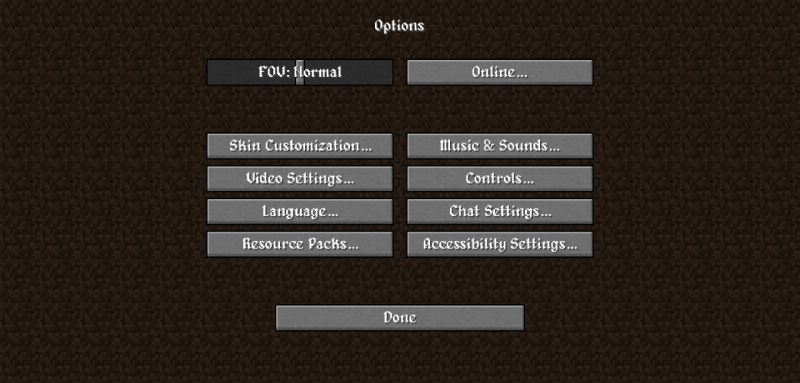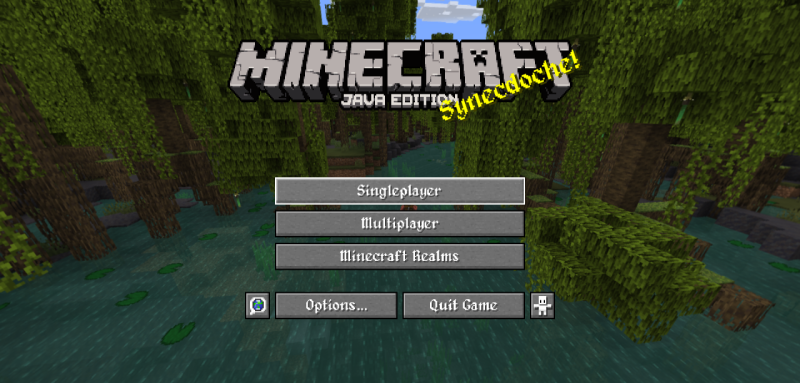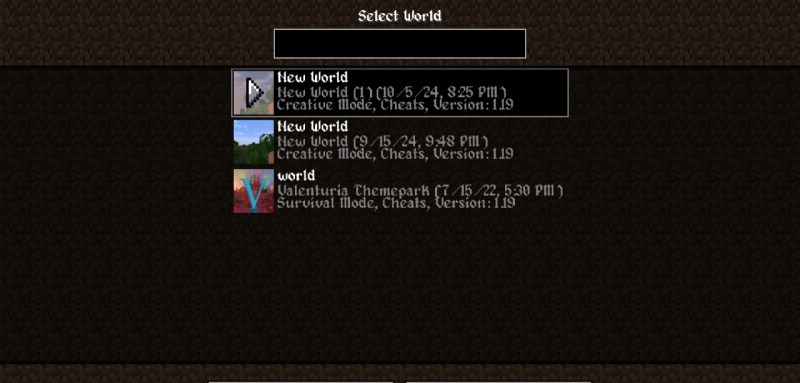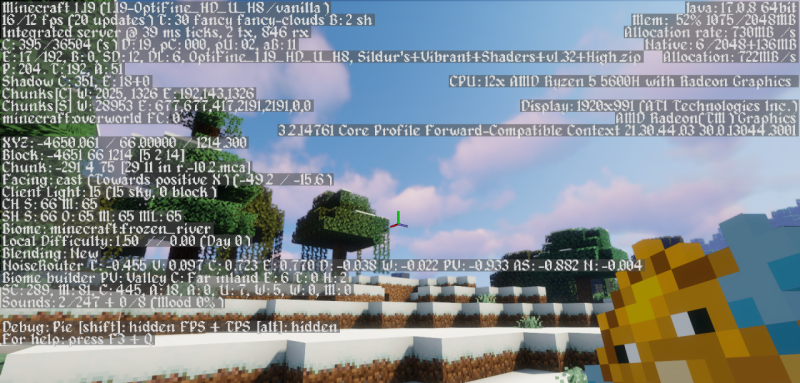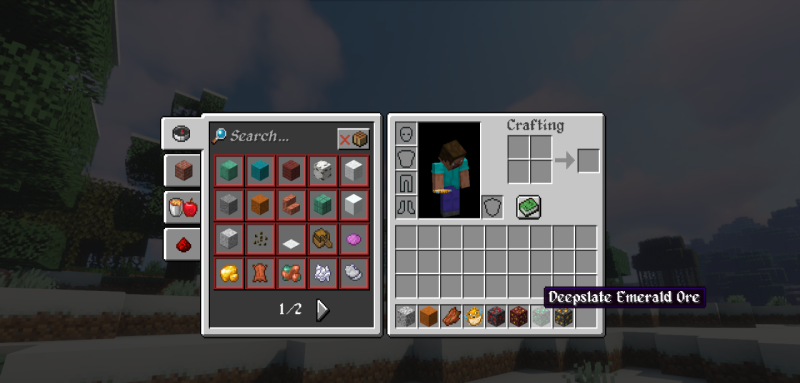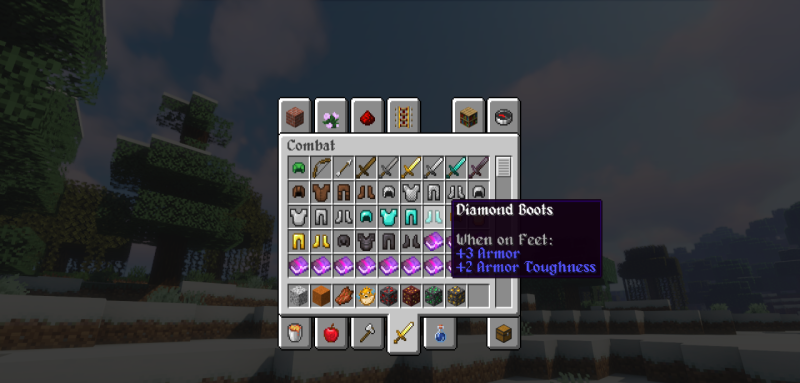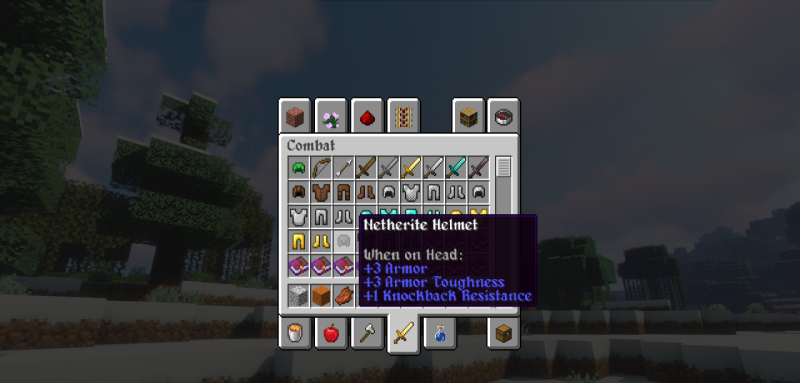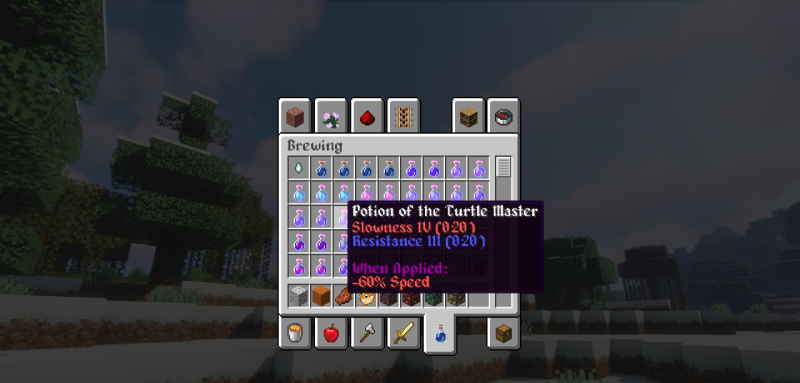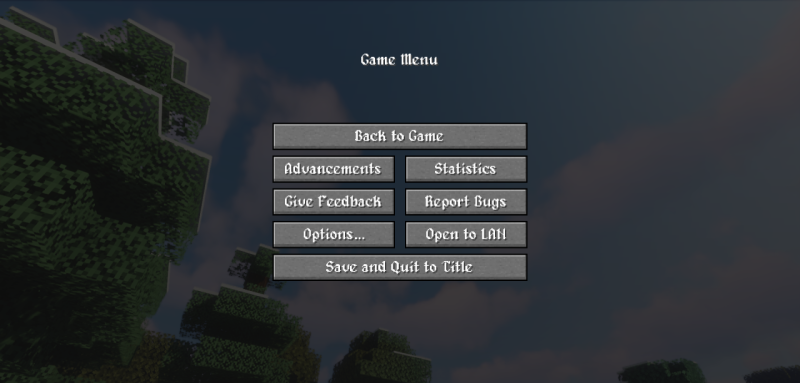
Alagard Font 1.20.1/1.19.4 (шрифт, стиль, оформление 16x)
Надоел стандартный шрифт Minecraft? Этот текстурпак заменит его на более проработанный и стильный вариант, который сделает интерфейс и тексты в игре более приятными глазу.
Шрифт выполнен в аккуратном, слегка готическом стиле, что добавляет игре нотку средневековья и уникальности. Отлично подходит для тех, кто хочет освежить внешний вид игры без кардинальных изменений.